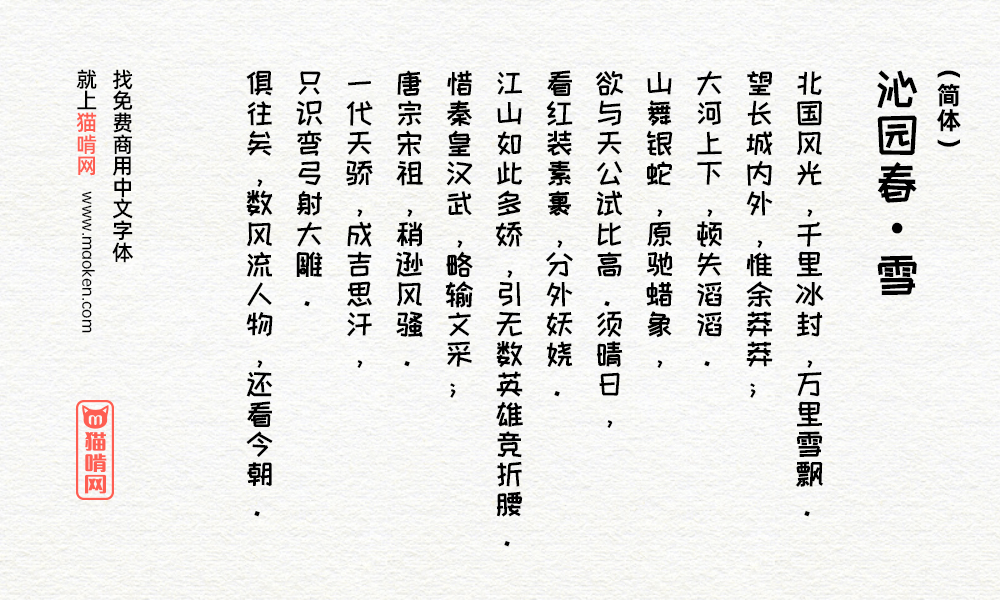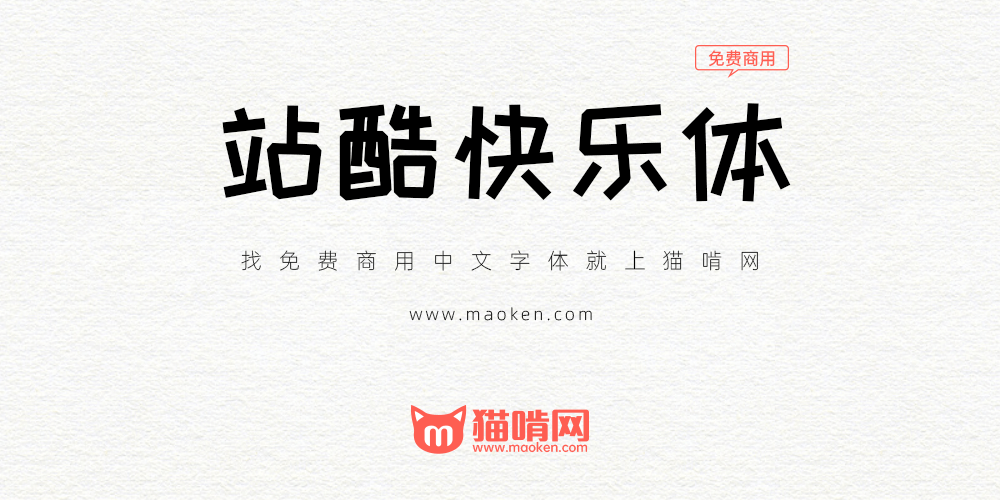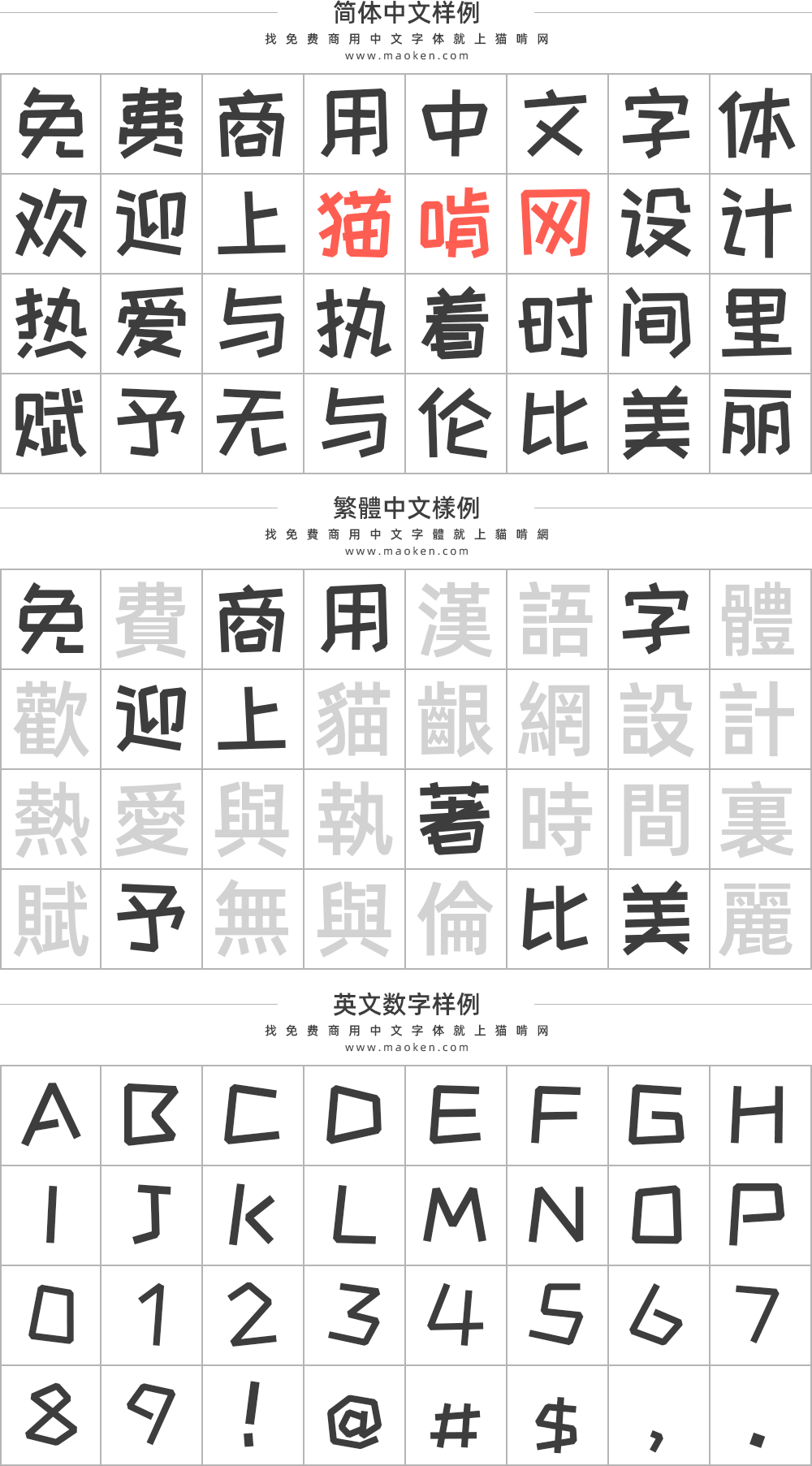
站酷快乐体由字体设计师刘兵克及100多位字体设计爱好者们共同完成。这套风格轻松活泼的字体也是继站酷高端黑之后,第二套由酷友集体创作完成,供所有人永久免费使用(可商用)的公益字体。
很显然,站酷快乐体,是一枚可爱有趣、活泼俏皮的个性字体。根据字体的形式特点,站酷快乐体可以很方便的应用在网页标题、促销主题、产品包装(如零售包装)等环境中,当然,你也可以用在漫画作品、电视节目这些环境里,只要你想用,就可以尽管用,因为站酷快乐体是免费的,是公益的,地球公民都可以任意使用!
关于站酷快乐体
【站酷快乐体】是由字体设计师刘兵克组织其字体设计学员进行的字体设计活动,由刘兵克提供字形框架和设计规范,由100多位学员朋友按照各自字体内容设计出基本字形,再由刘兵克字体设计工作室成员杨康和吴少杰进行设计修改和调整完成。发布于2015年9月。
【站酷快乐体2016修订版】,是在“站酷快乐体”基础上进行的大幅修改与提升, 本次修订工作的设计前期,由刘兵克学员团队和工作室团队共同完成,设计后期,由刘兵克进行了逐一修改与调整,经过多轮校审之后,于2016年6月正式对外公布和提供下载,整个工作耗时7个月。
★【站酷快乐体2016修订版】,采用GB2312汉字编码,共收录6763个汉字。
应用示例
- 开源版的站酷快乐体更新版本,修复一些字体的问题。
Ver 3.53(2021/12/24)
- 修改“膈涎锴嗖恫劓巅遥害赜碡”
Ver 3.52(2021/10/13)
- 修改:“畿袜”二字
Ver 3.51(2021/08/12)
- 修正“怄”字
Ver 3.50(2021/07/14)
- 站酷设计师@skr_ZERO子继续对字体进行修正。
- 为了与站酷版区分开,将版本号改为3.50,这样就不用再问哪个更新了
- 改动“蒸逸榔隆窿榘撅诶嗳嫒嵫袱”12字的错误
- “畿”去黑块
- “又攵夂攴”等部件里捺不出头的问题就让他一直存在吧,我将“夏”字还有几个“犭”旁的字都还原了
- 只改“烙酪寇”三字
Ver 2.00(2021/06/19)
- 站酷设计师@skr_ZERO子继续对字体进行修正。
- 发现“狰”和“挣”太相近,于是把“狰”改了,顺便改了几个“犭”旁的字。
Ver 2.00(2021/05/13)
- 2021年5月13日,站酷设计师@skr_ZERO子发布站酷快乐体部分汉字字形问题依旧存在,于是便进行了修正并发布了新的版本。
- 31字字形错误:廊郡盟儒狰蒸逸榔隆窿榘撅诶嗳嫒嵫袱烙酪寇袜膈涎锴嗖恫劓巅遥害赜
- 6字轮廓有问题:腐蚯螓貘畿碡
- 68字字形错位:馇恽饪忾狲馔馀恻馄饨恺怃饩狍怄馑狯饷馓恸饽猬廪恹犷饧忏馍惬饬犸馐怆猡饴怿猕赓馊悭饫怅猃馕庑钛钌睐钚钊眦钕钋眍钗钇钫钔钆钤钐羁钣钏罴钜钍睑
- 改动7个标点符号的字形、位置:、。,:;!?
Ver 2.00(2018/11/20)
Ver 1.00(2016/06/01)
- 站酷快乐体2016修订版正式对外公布和提供下载,整个工作耗时7个月。
Ver 1.00(2015/09/01)
- 站酷快乐体对外发布